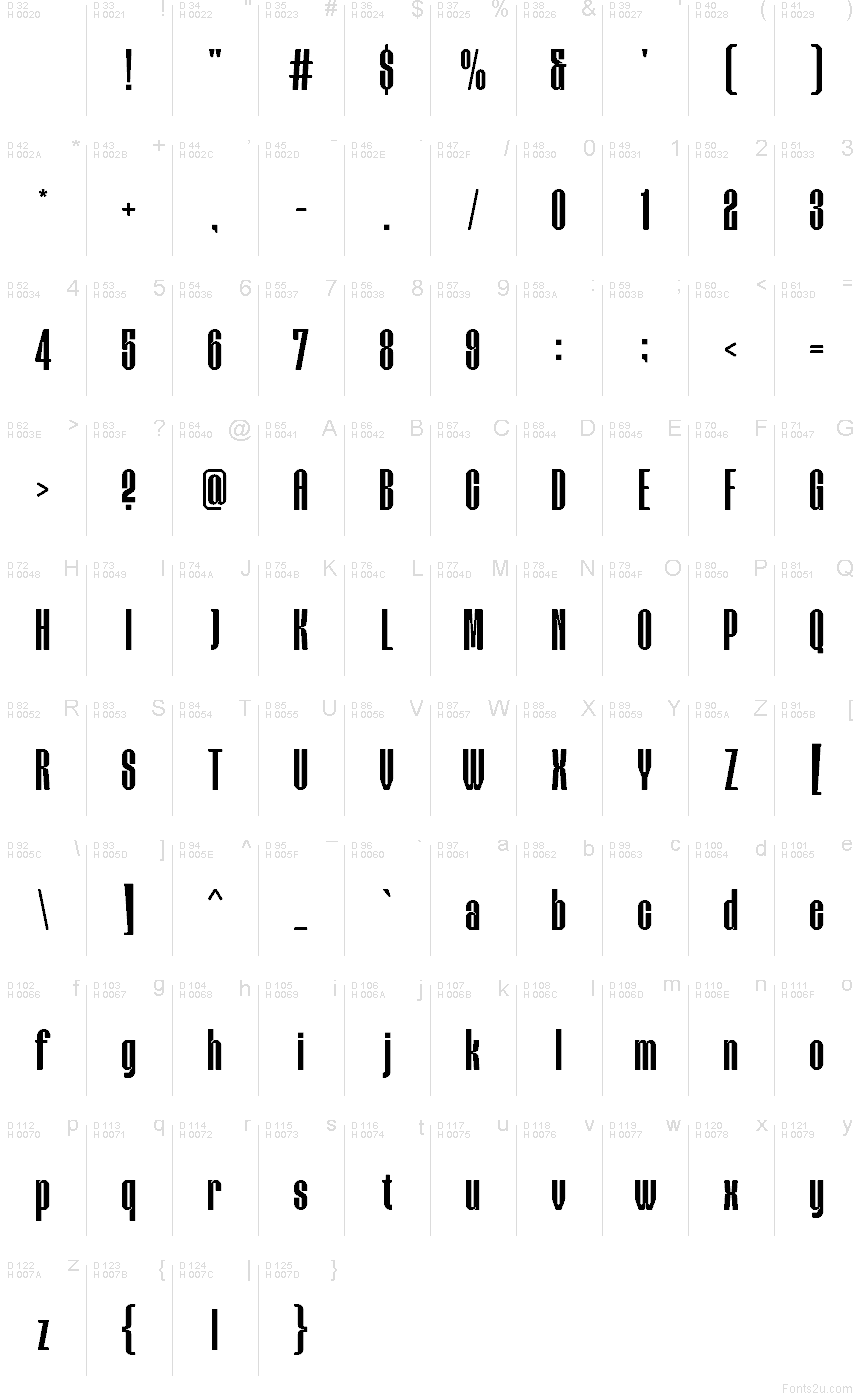
Saikro, da Ermedia Studio, é uma fonte display retrô gratuita com letras excepcionalmente altas e estreitas e traços verticais encorpados. As partes superiores arredondadas suavizam as formas densamente comprimidas. Aberturas internas estreitas e pequenas bases alargadas acrescentam detalhes a um desenho que, de outro modo, seria denso e vertical.
Como ponto focal teatral, o letreiramento se presta a pôsteres de shows, embalagens de discos e letreiros de bares, onde suas proporções exageradas remetem ao grafismo vintage do entretenimento. As letras imponentes podem se transformar em formas arquitetônicas dentro de um cenário urbano ilustrado.